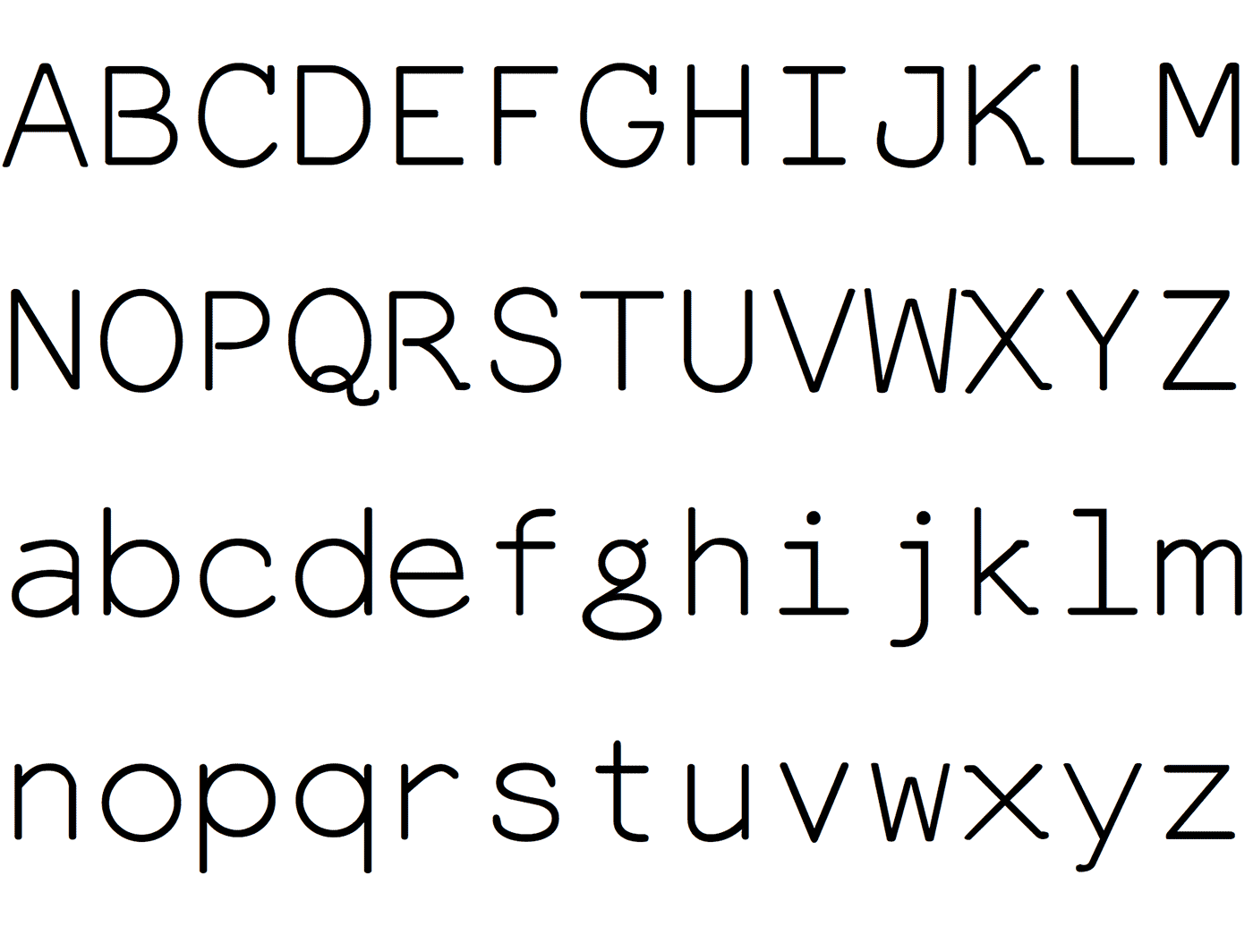
- 1994
- Antiqua dekorativ
- Versaleszett:
- enthalten
Michael Everson beschreibt seine dicktengleiche Schrift als einfachen, aber eleganten Font, desses Ziel es ist, alle Zeichen von Unicode beziehungsweise ISO/IEC 10646 (bis auf Han-Chinesisch) darstellbar zu machen. Der Designer schlägt die Schrift auch ausdrücklich als Alternative für Systemfonts wie Courier (New) und Monaco vor.